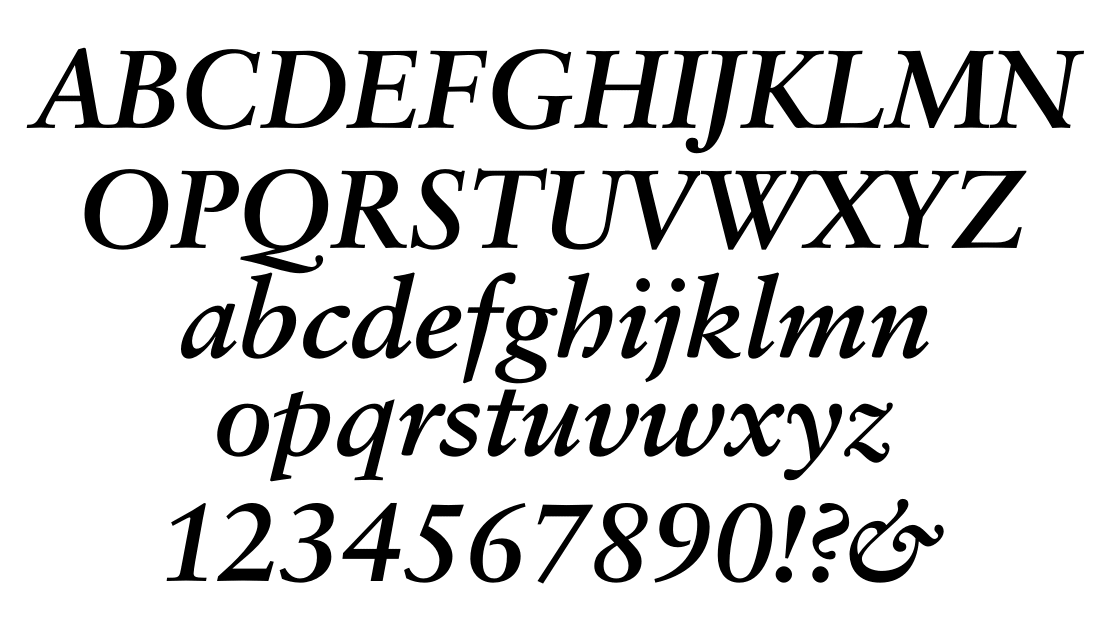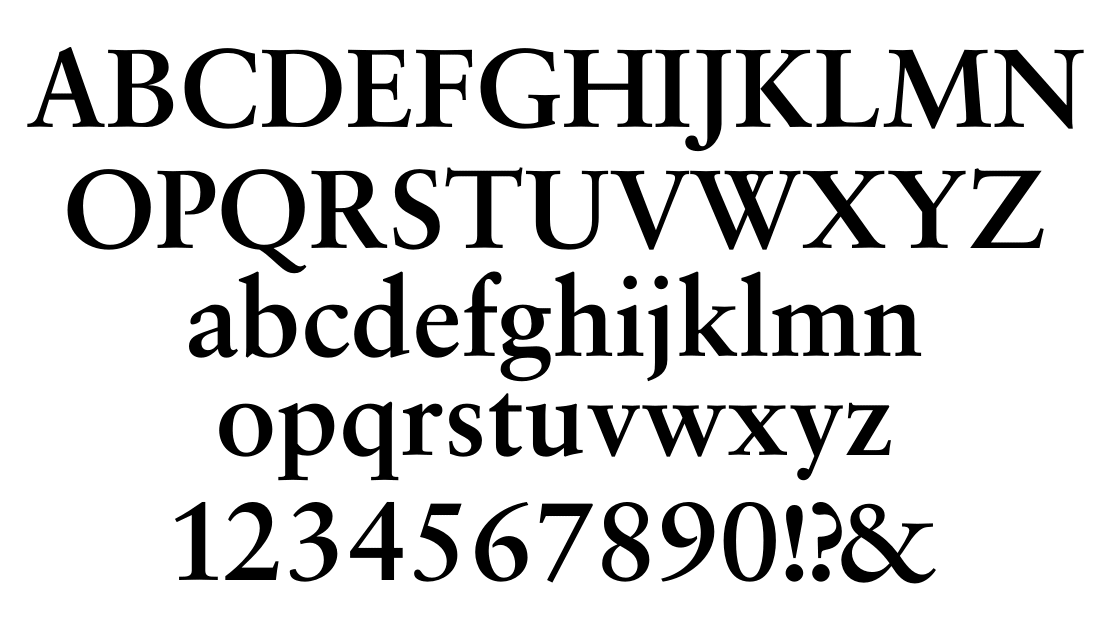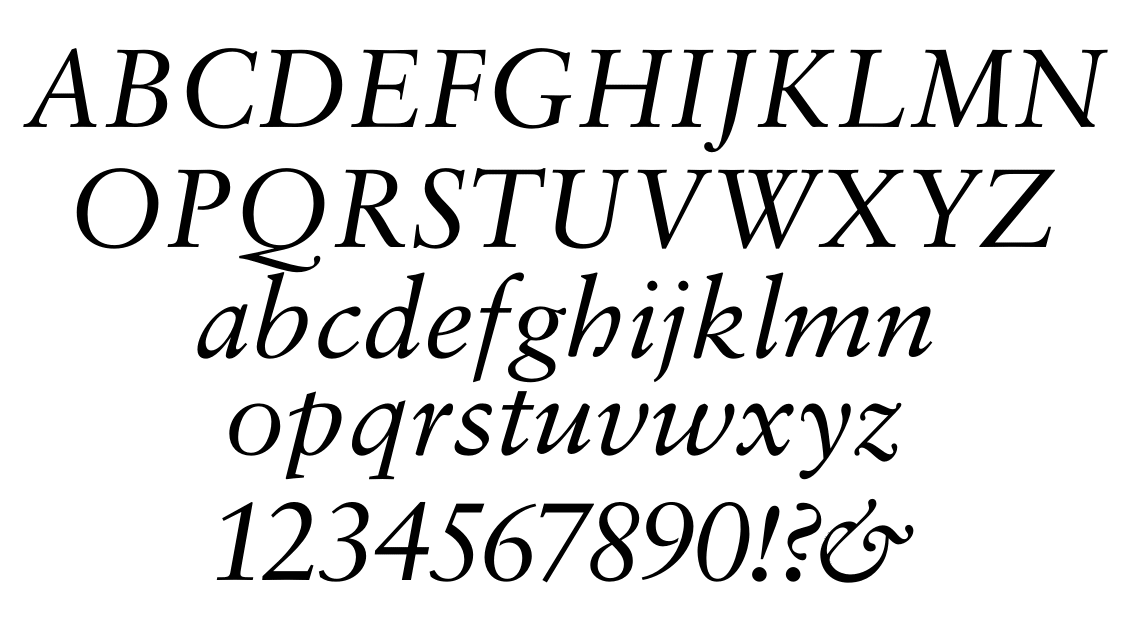
★Sabon
Designer
Jan Tschichold (1902–1974)
Date
1964–1967
Sabon Next
Designer
Jean François Porchez (1964–)
Date
2002
Garamond をベースにしたヤン・チヒョルトによる書体「サボン」。 1964年に着手され、67年に Linotype, Monotype, Stempel の3社からリリースされたが、それぞれ微妙にデザインが異なるようである。 名称はフランスの活字鋳造業者 Jacques Sabon (1535–1590)にちなむ。